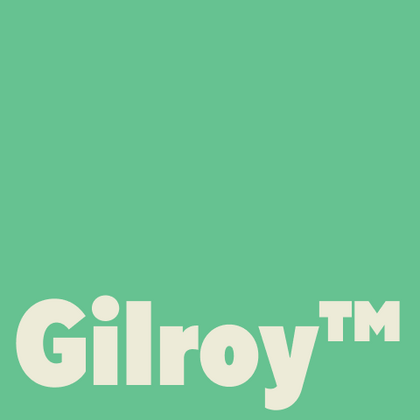
Шрифты похожие на Gilroy™
В поисках современного геометрического гротеска в нашей коллекции вы найдете стильные альтернативы, которые сохраняют четкость линий, но при этом выглядят свежо и оригинально. Если вам близок шрифт Gilroy™, обратите внимание на наши разработки — они предлагают аналогичную эстетику.
Если вы устали от «заезженных» шрифтов и ищете гарнитуры, похожие на Gilroy™, ознакомьтесь с нашими лучшими альтернативами Gilroy™. Это шрифты, которые имеют близкие характеристики, но в то же время обладают новыми уникальными особенностями дизайна. Например, относятся к той же категории шрифтов, подходят для тех же целей и имеют похожие черты, но отличаются в деталях или пропорциях.
Найдите отличную замену Gilroy™ и попытайтесь имитировать похожее настроение, передать нужное вам ощущение, используя его в своих проектах. Каждый шрифт, представленный на этой странице, является двойником шрифта Gilroy™, фактически его полным аналогом.
TT Neoris — лаконичный неогротеск с безграничными возможностями. Мы уделили особое внимание деталям, cделали наклонные начертания в кириллице визуально отличными от латиницы, соответствующими традиции кириллической каллиграфии.
TT Chocolates — изящный гуманистический гротеск сo сбалансированными пропорциями, близкими к классическим. Шрифт с приятным дружелюбным характером, который интуитивно воспринимается как что-то знакомое.
TT Wellingtons — это гуманистический гротеск, формы которого отсылают к движению ширококонечного пера. Пластичные линии букв обновлённой гарнитуры, присущие английским гуманистическим шрифтам XX века, выглядят актуально и живо в современных дизайнерских проектах.
TT Rounds Neue — гротеск со скругленными формами. В тонких начертаниях шрифт выглядит довольно минималистично и нейтрально: скругленные окончания штрихов становятся практически незаметными, на первый план выходят плавные линии.
TT Commons™ Classic является универсальным гротеском с минимальным контрастом штрихов, закрытой апертурой и геометрическими формами знаков. Дизайн гарнитуры разрабатывался для максимально широкого круга задач, с которыми обязан справляться любой качественный корпоративный шрифт.
TT Prosto Sans является шрифтовой гарнитурой на любой жизненный случай. Благодаря современным открытым гротескным формам, вы можете использовать гарнитуру почти для любой задачи.